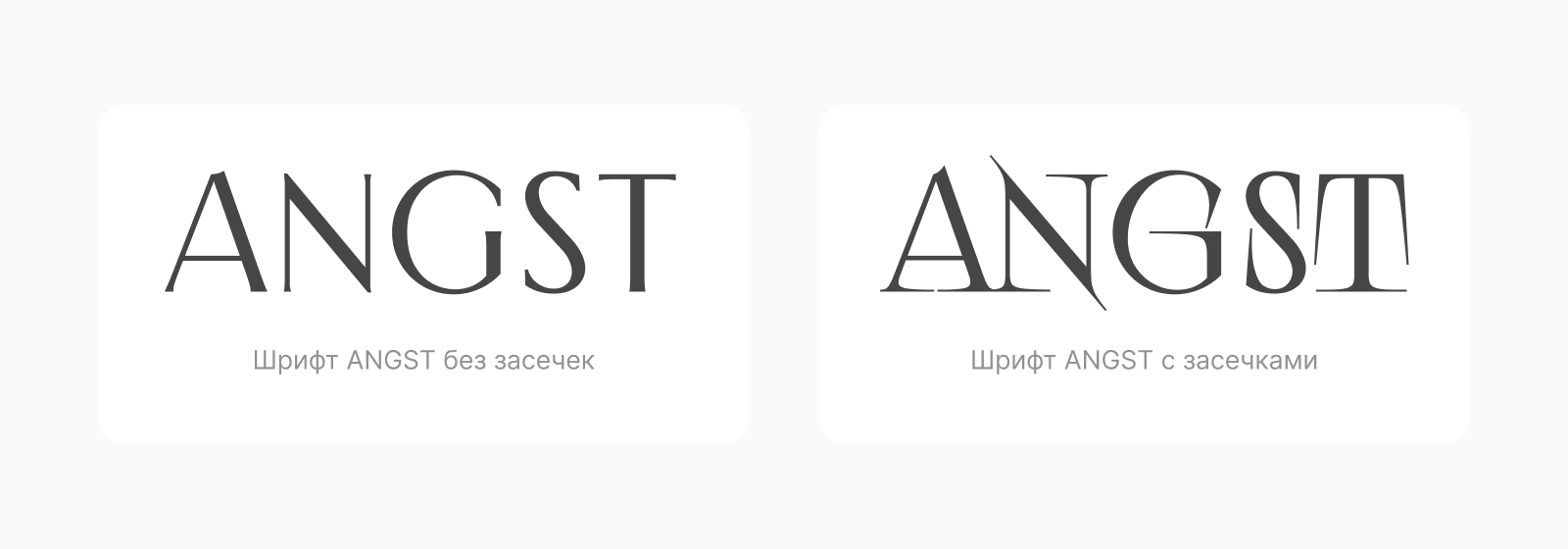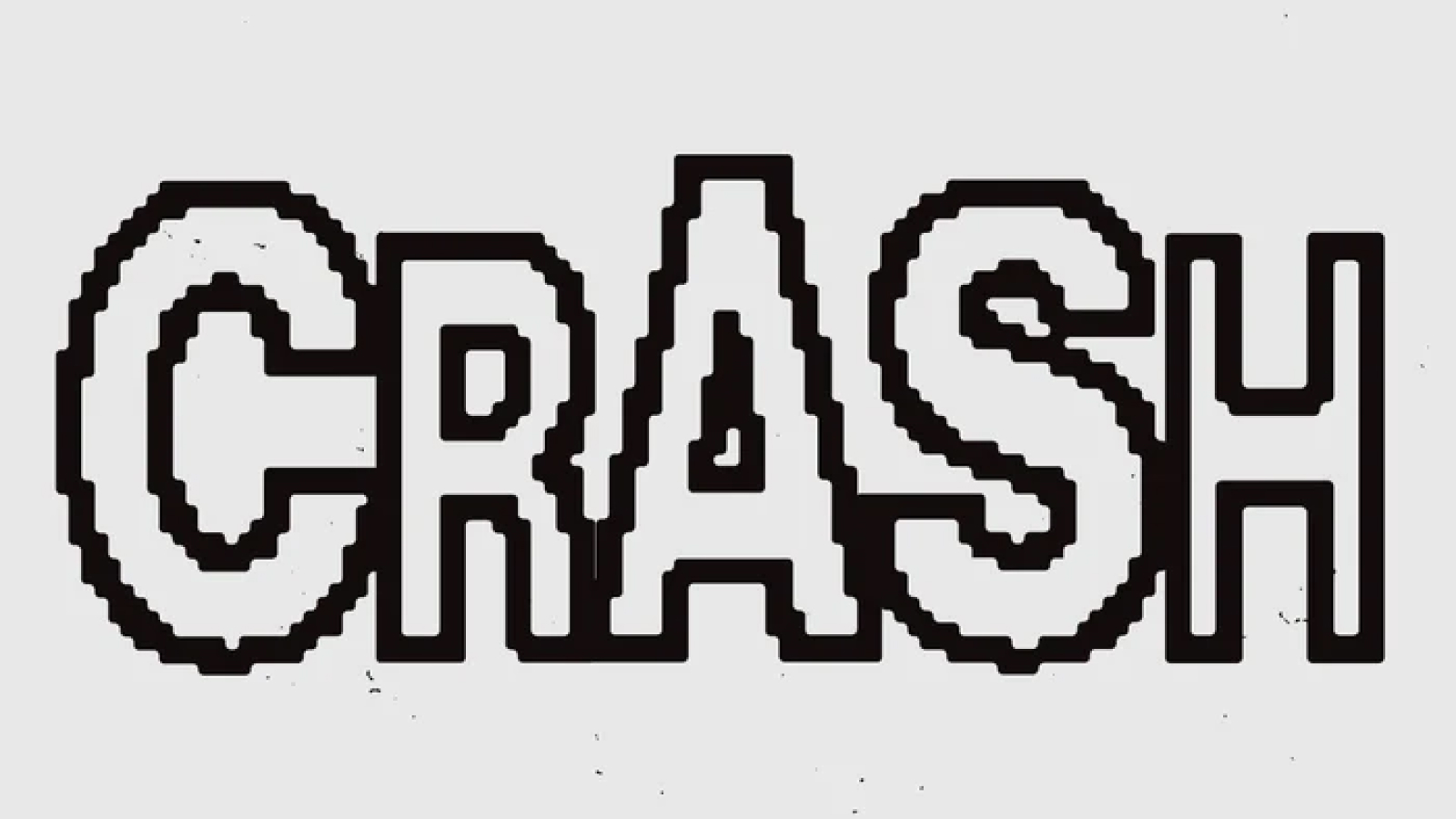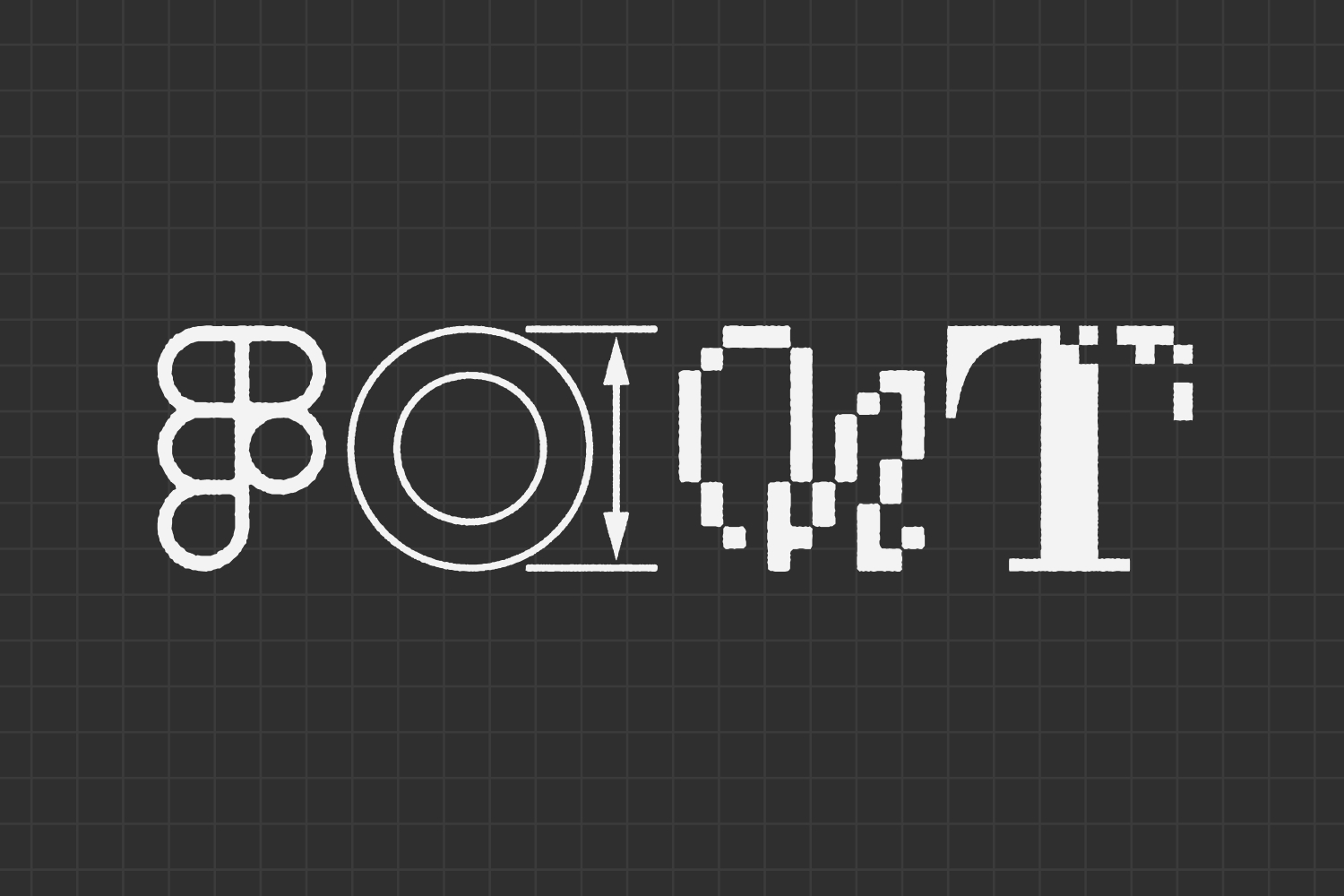
Трендовые шрифты 2026: что будет формировать типографику завтра?
Типографика всегда была больше чем просто буквы на экране. Это первое впечатление, которое получает пользователь.
В этой статье мы не просто перечислим трендовые шрифты 2026 года — мы разберём, откуда они взялись, почему они важны, и самое главное, как применять их в реальных проектах, не жертвуя юзабилити. Погнали!
Мейнстрим вариативных шрифтов
Вариативные шрифты (variable fonts) — это технология, которая позволяет упаковать множество начертаний одного шрифта в один файл. Вместо того, чтобы загружать отдельные файлы для Regular, Bold, Light и Italic, вы получаете один файл, внутри которого можно плавно менять параметры: толщину (weight), ширину (width), наклон (slant) и даже кастомные оси. Например, как в шрифте ANGST, который мы использовали в одном из нашх видео, мы можем регулировать длину засечек.
Вариативный шрифт ANGST и его настройки
Если в 2024-2025 годах вариативные шрифты были нишевым инструментом, то в 2026-м они становятся стандартом индустрии. Почему? Потому что они решают сразу несколько проблем дизайнеров.
- Производительность веба. Один файл вместо десяти — это быстрее загружается, меньше весит и лучше для пользователей с медленным интернетом.
- Гибкость в дизайне. Адаптивная типографика становится реальностью. Вы можете программно менять толщину шрифта в зависимости от размера экрана или контраста фона. Представьте: на маленьком экране шрифт автоматически становится чуть жирнее для лучшей читабельности.
Возвращение к серифам: бунт против однообразия
Последние несколько лет мы наблюдали экспансию гротесков. Логотипы крупных брендов один за другим становились минималистичными сан-серифами. Google, Airbnb, Uber — все упростили типографику до предела. И знаете что? Людям это надоело.
Эволюция логотипа Google
Когда все бренды выглядят одинаково, теряется индивидуальность. Creative Boom отмечает, что дизайнеры всё чаще говорят о «гомогенизации сан-серифов» — логотипы становятся неотличимыми друг от друга.
Поэтому шрифты с засечками становяться все популярнее. Даже на сайте Белого дома используется супер трендовый Instrument Serif. Как жаль, что данный шрифт не поддерживает кириллицу. Хотя, можно добиться похожего эффекта у кириллического шрифта, при помощи плагинов в Figma. На бесплатном курсе “Графический дизайн: старт в профессии” Никита вам рассказывал, как это сделать.
Интерфейс Savor в котором используется Serif шрифт
Не бойтесь миксовать — используйте серифы для заголовков в паре с чистым гротеском для основного текста. Это создаёт визуальную иерархию и добавляет индивидуальности. Главное следите за контрастом и размером.
Хаотическая типографика и несовершенные формы
Хаотическая типографика — это не случайный беспорядок, а осознанное решение создать эмоциональный отклик. Это буквы, которые выглядят так, будто их разбросали по холсту. Разный размер, угол наклона, перекрытие элементов — всё это создаёт ощущение спонтанности и энергии.
Шрифт Crash от Type Mania
Studio2am описывает это как «визуальный джаз» — вы нарушаете правила, чтобы создать что-то неожиданное и захватывающее. Даже Figma разработали свой хаотичный шрифт, который они раздавали на Config 2025, и которым мы делились с вами в этом видео.
Шрифт Practice Type от Figma
В мире, где всё выглядит одинаково гладко и отполировано, хаос выделяется. Это работает особенно хорошо для брендов, которые хотят казаться молодыми, смелыми и не такими как все.
Доступность: не тренд, а необходимость
Инклюзивная типографика — это не просто модное слово, это стандарт качественного дизайна.
NNGroup ссылаются на данные CDC, в которых говориться, что 61 миллион взрослых в США живут с инвалидностью. Это огромная аудитория, которую нельзя игнорировать. Но доступная типографика помогает не только людям с особыми потребностями — она делает интерфейсы лучше для всех.
Ключевые принципы доступной типографики
- Контраст. WCAG рекомендует соотношение контраста минимум 4.5:1 для обычного текста и 3:1 для крупного текста. Используйте контраст чекер на сайте Академии для проверки и создания доступных интерфейсов.
- Размер. Минимальный размер основного текста — 16px. Помните, что с возрастом зрение ухудшается, и то, что кажется вам нормальным, может быть слишком мелким для других. Nielsen Norman Group подчёркивает, что размер шрифта должен быть достаточным, и пользователи должны иметь возможность его менять.
- Избегайте All Caps для длинных текстов. Хотя исследования показывают, что заглавные буквы могут быть эффективны для быстрого сканирования отдельных слов, для длинных текстов они снижают читабельность.
Самое важное — не гнаться за всеми трендами сразу. Трендовые шрифты 2026 — это хорошо, но выберите те шрифты, которые соответствуют вашему проекту, вашей аудитории и вашим целям. Экспериментируйте, но всегда помните про usability и ставьте его на первое место.
Лучший шрифт — это тот, который пользователь не замечает, потому что он идеально выполняет свою функцию. Хотя иногда шрифт должен кричать, плавиться и танцевать — и это тоже нормально. Главное знать, когда и зачем.